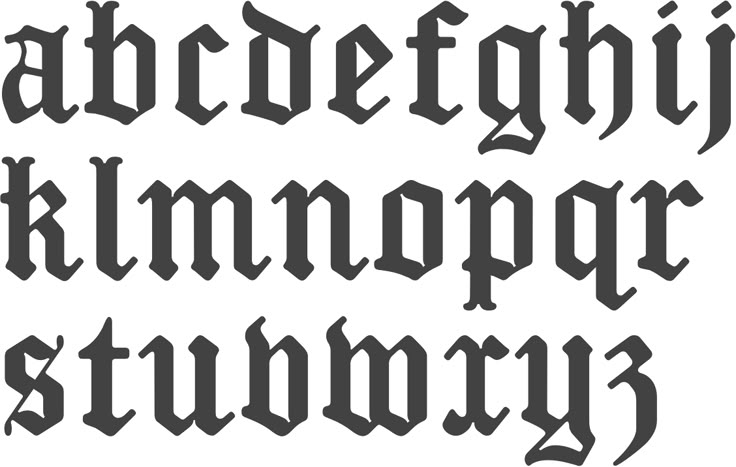
21 шрифт для создания пугающих дизайнов
Хэллоуин — веселый праздник. Он ассоциируется с вечеринками, яркими декорациями, мероприятиями и развлечениями.
Мы собрали для вас эту коллекцию жутких шрифтов, чтобы вам было проще создавать по-настоящему пугающие приглашения, открытки, баннеры, декорации и т.д.
Здесь представлены разные стили, при этом все шрифты являются уникальными, жуткими, драматичными, и могут быть использованы в любом проекте, связанном с темой ужасов. Так что если вы работаете над классным постером, забавными приглашениями, обложкой книги или компьютерной игрой, вы можете найти подходящий шрифт в нашем списке.
Шрифты передают тон и характер вашего контента. Вот почему важно найти идеальный вариант, который будет вызывать у аудитории нужные ощущения. Мы выбрали как бесплатные, так и платные смелые, эффектные, грубые, креативные и выразительные шрифты, способные поднять ваш проект на новый уровень. Итак, давайте рассмотрим их подробнее:
1.
Dreadful + дополнительные материалы
Dreadful — красивый винтажный шрифт. Кажется, будто вы видели его в старых фильмах и комиксах. Массивные эффектные буквы доступны в 4 стилях, каждый из которых подойдет для книг, постеров, баннеров, заголовков или приложений.
Покупатель получит тщательно продуманный выразительный шрифт, а также набор интересных графических материалов на тему Хэллоуина — все, что вам потребуется для создания пугающего дизайна.
2. Exorcist
Exorcist — декоративный заметный шрифт, который будет отлично смотреться на плакатах, открытках, баннерах, приглашениях и флаерах. Его можно назвать геометрическим и грубым.
Он идеально подойдет для создания пугающих, интересных, драматичных обложек книг и постеров. Шрифт выглядит современно, однако содержит элементы винтажного стиля. Exorcist состоит из заглавных букв, цифр и знаков препинания.
3. Horror
Именно подобные шрифты мы привыкли видеть в фильмах ужасов. Horror выглядит стильным и простым, но в то же время впечатляющим и пугающим.
Благодаря штрихам неправильной формы, он кажется рукописным. С помощью этого шрифта вы можете сделать любой дизайн устрашающим и интересным. Скачайте его бесплатно и добавьте жуткий штрих в свои творческие проекты.
4. Ghoulish Font
Ghoulish Font — пугающий шрифт с засечками. Он состоит из массивных неровных букв в винтажном стиле. С помощью такого шрифта можно создать привлекающий внимание заголовок или впечатляющий логотип. В целом, это профессиональный смелый шрифт, который сделает дизайн уникальным и пугающим.
5. Story Brush
Если вы искали рукописный шрифт, нарисованный кистью, этот вариант точно для вас. Эффектный профессиональный шрифт будто был разработан специально для ужастиков. Покупатель получает 2 разные версии и 240 глифов, которые позволят добавить в проект стремительность и импульсивность.
Story Brush — это забавный, живой шрифт для постеров, логотипов или футболок на Хэллоуин.
6. Chiller
Внешний вид Chiller (от слова “chill” — отдыхать, расслабляться) полностью соответствует его названию — штрихи выглядят просто и расслабленно.
Этот рукописный шрифт смотрится естественно и способен сделать ваш пугающий дизайн минималистичным и реалистичным.
В набор входят интересные графические материалы и альтернативные глифы, которые пригодятся в работе над творческими проектами. Используйте этот шрифт для реализации драматических и необычных концепций.
7. Real Horror Font
Реалистичный шрифт с царапинами и рельефными штрихами может добавить проекту уникальности. Если вы хотите, чтобы дизайн выглядел естественно и убедительно, Real Horror — отличный выбор. Он состоит из заостренных рукописных букв, которые кажутся оригинальными и пугающими.
Такой шрифт отлично впишется в дизайн, наполненный порезами, ранами, отметинами и царапинами. Добавьте его в свою коллекцию и обязательно используйте в следующих проектах, посвященных теме Хэллоуина.
8. No Mercy Font
Уникальный шрифт. Он, несомненно, выглядит привлекательным и современным. Глифы будто небрежно заштрихованы ручкой. Смелый, свободный, уверенный стиль отлично подходит для дизайнов, связанных с ужасами.
Используйте его, чтобы придать заголовкам эффектный необычный вид.
9. Blood Of Dracula Font
Классический шрифт в староанглийском стиле, напоминающий стекающую кровь. На странице загрузки вы можете увидеть множество логотипов, в которых он был использован. Скачайте его бесплатно и сделайте свой дизайн винтажным и эффектным. Благодаря каплям, шрифт выглядит динамично и устрашающе. Он впишется как в современный, так и в ретро-дизайн.
10. Halloween Spider
Halloween Spider — шрифт из заглавных букв с уникальным дизайном. Он смелый, креативный и идеально подходит для любого дизайна на тему Хэллоуина, постеров, игр и брендинга. Изображения паутины и пауков хитроумно встроены в каждую букву, благодаря чему непримечательный шрифт без засечек становится интересным и пугающим.